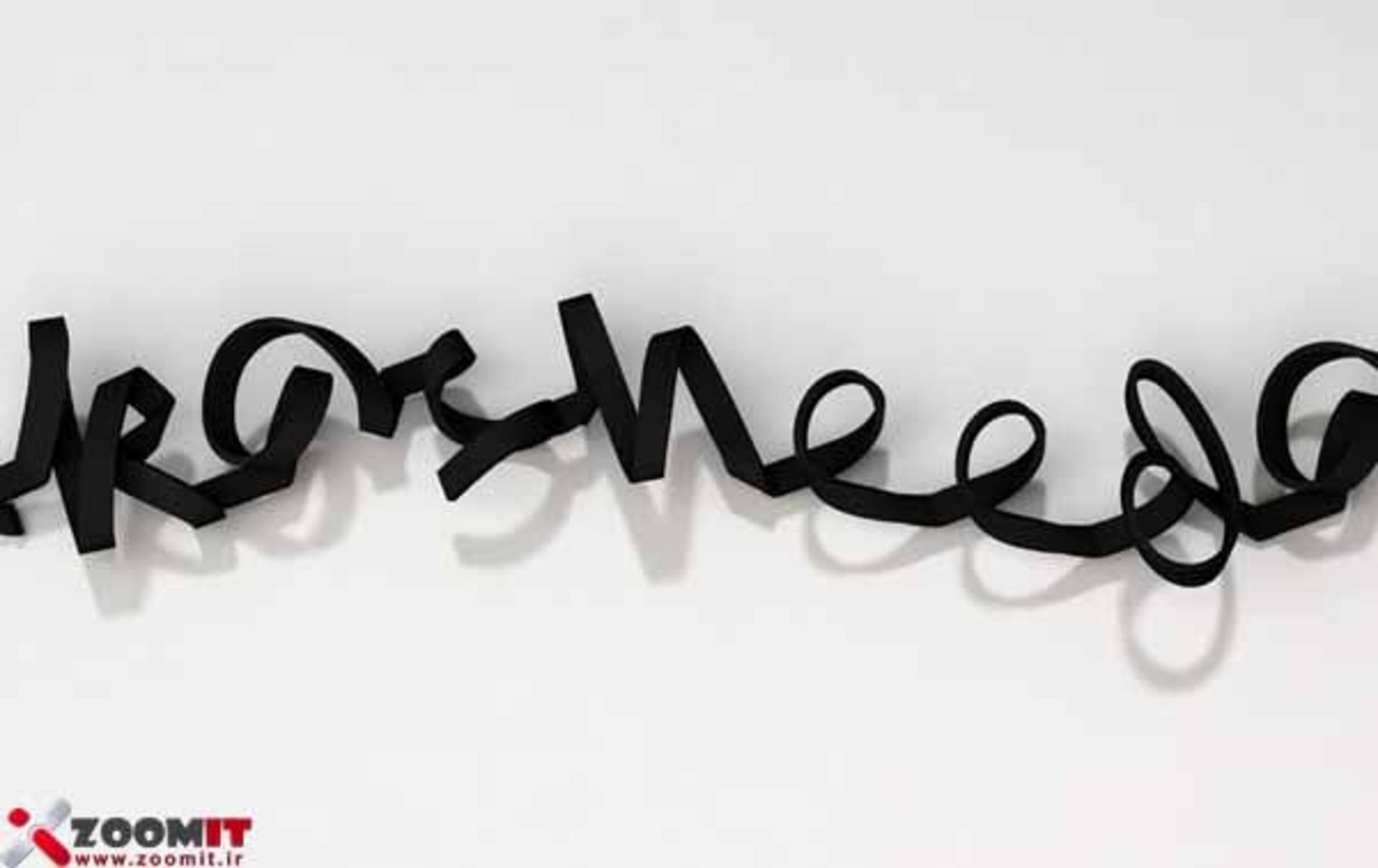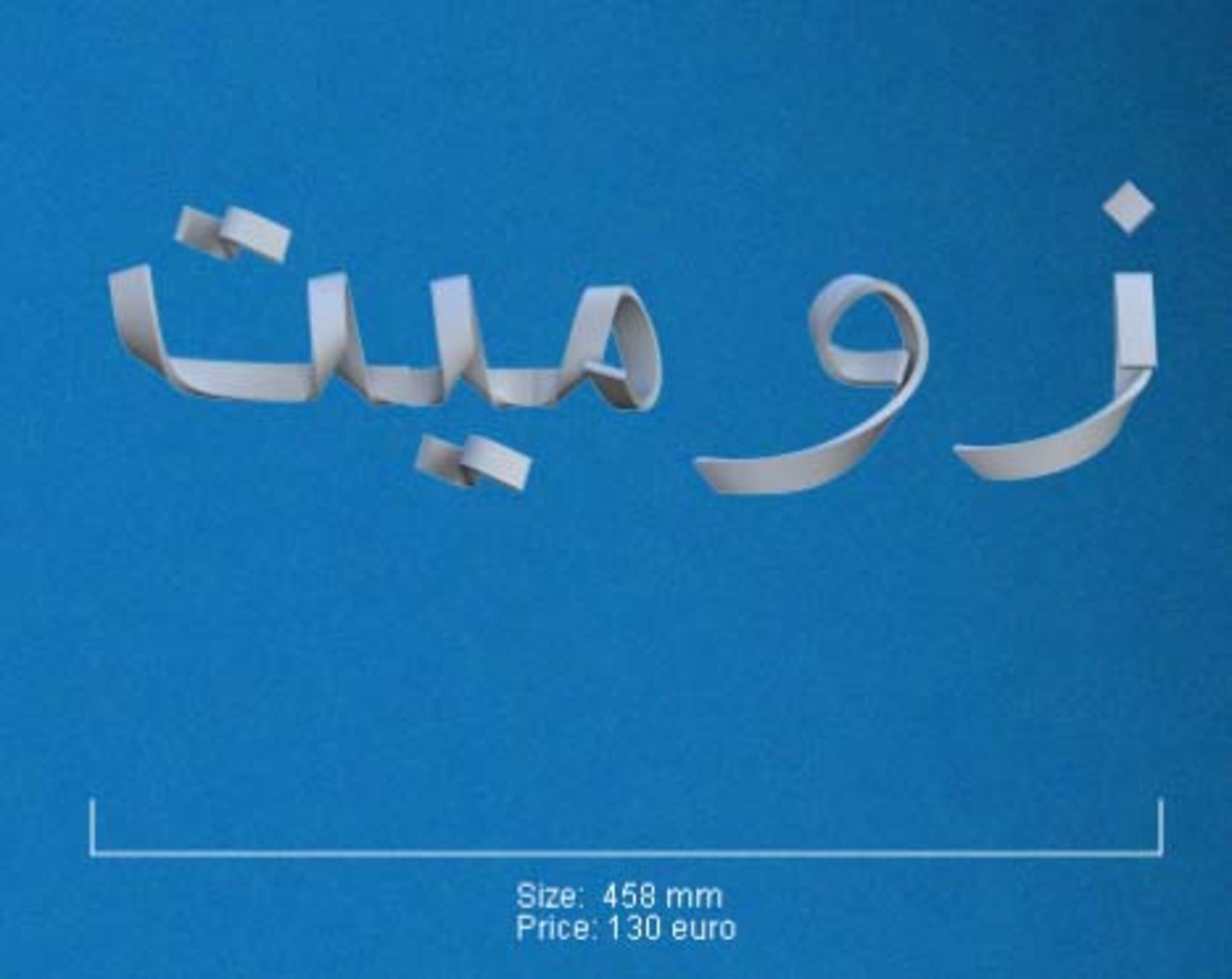
توسط سایت Freedom of Creation هر کلمه ای که میخواهید را سه بعدی پرینت بگیرید
کل کاری که باید انجام دهید این است که حروف مورد نظرتان را در وب سایت Creation's Website تایپ کنید. این وب سایت هم با استفاده از یک پرینتر سه بعدی، کلمه مورد نظر شما را پرینت می گیرد تا بتوانید از آن بر روی میز یا جلوی درب اتاقتان استفاده کنید.
این سایت می تواند کلمه مورد نظر را به دو صورت عربی و لاتین دریافت کند. متن شما به صورت یک نوار پیچانیده شده در می آید . این خلاقیت (نه چندان جالب) توسط Melle Hammer و Yara Khooury خلق شده است.
البته این سایت در ابتدا تنها ظاهر متن را به شما نشان می دهد ولی هزینه لازم برای پرینت این متن را باید بپردازید تا متن پرینت شده برای شما ارسال گردد. ظاهرا هزینه آن هم کم نیست. به طور مثال برای پرینت سه بعدی کلمه "زویمت" هزینه ناچیز 130 یورو باید پرداخت شود.
این نوشته سه بعدی آن قدر جذاب نیست که بخواهید هزینه زیادی بابت آن پرداخت کنید. پس تصور می کنیم خالقان این اختراع باید به دنبال کسب درآمد از روش دیگری باشند.